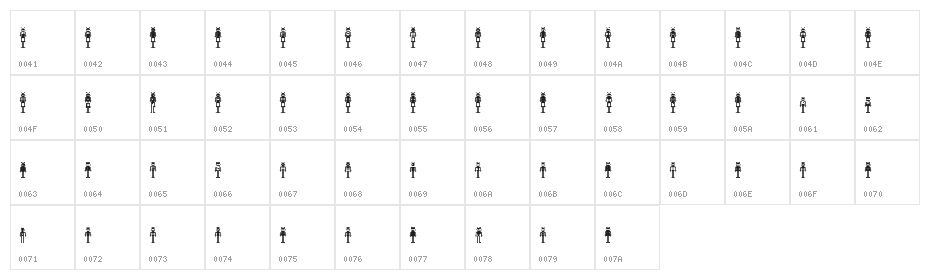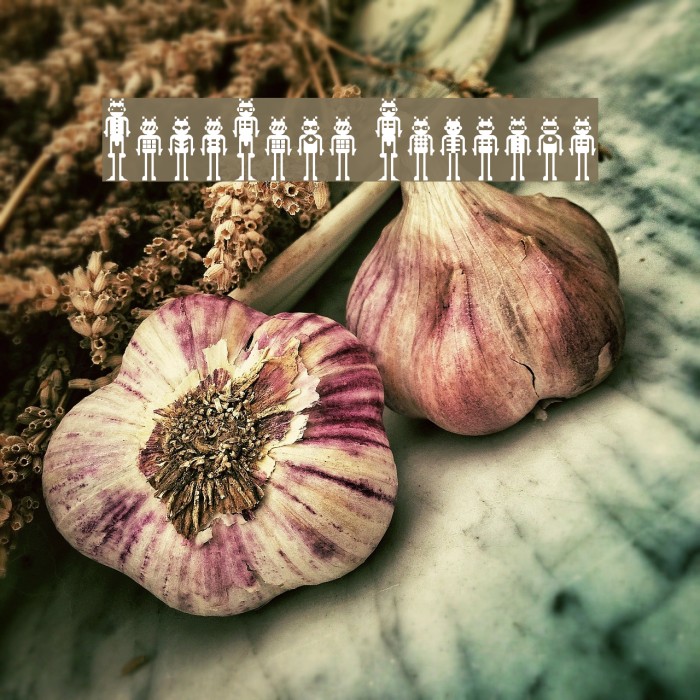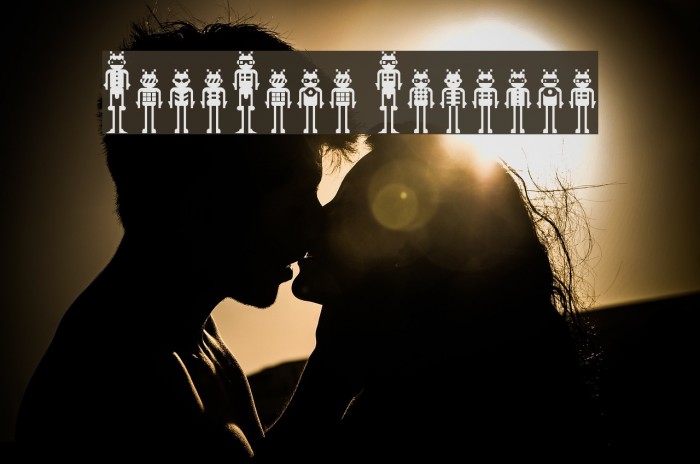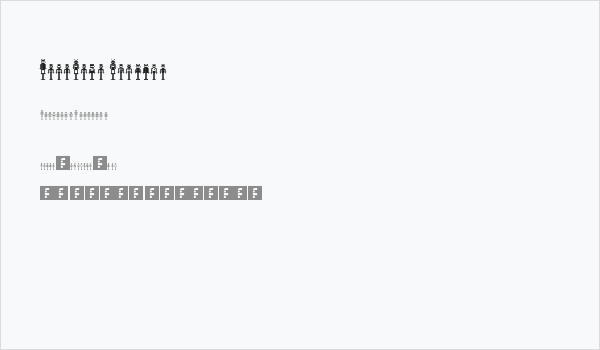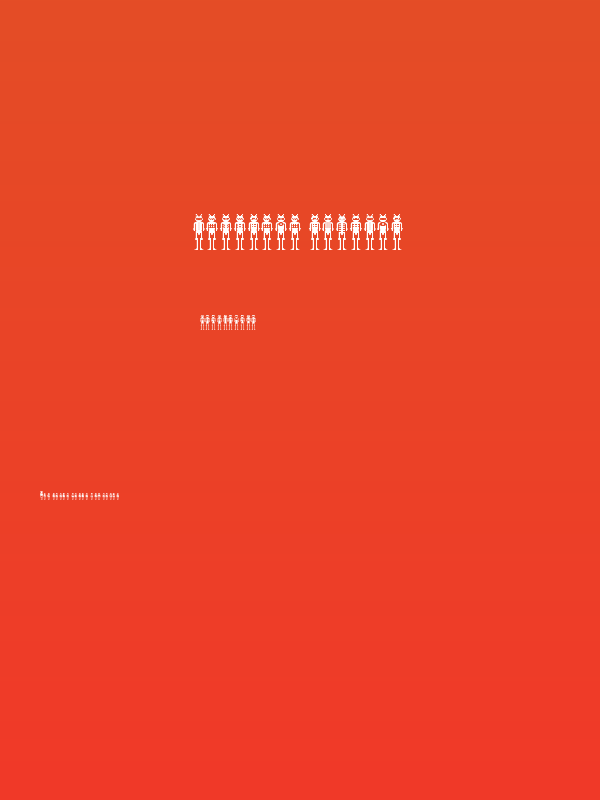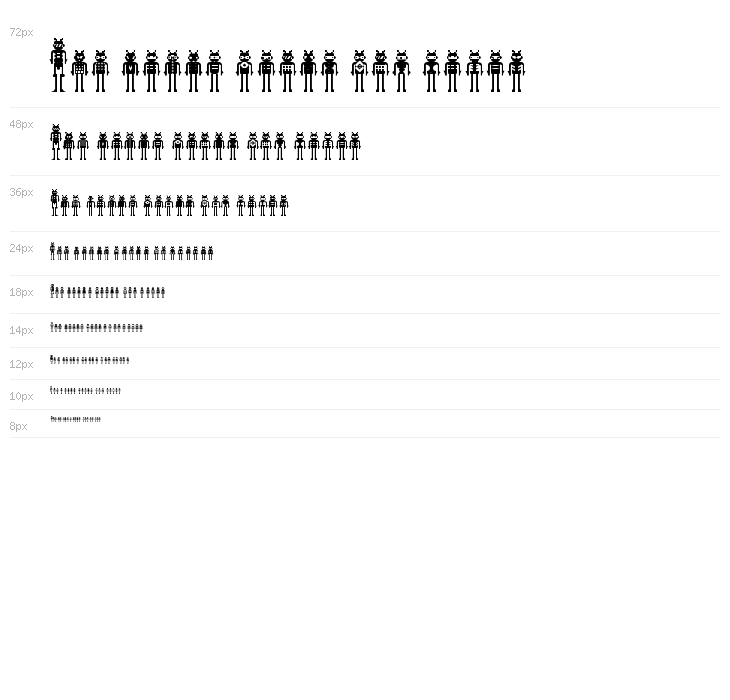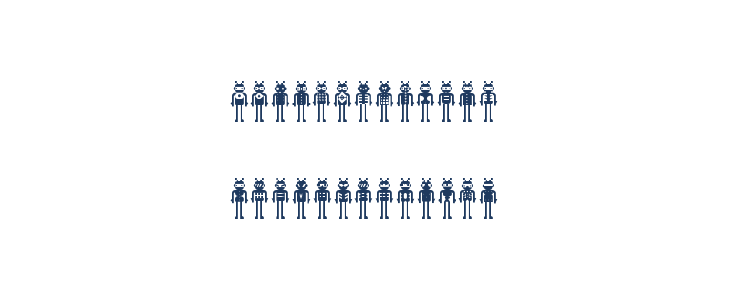
LostRobo Regular Font
| Stile generale | Futuristic, Playful |
| Caso d'uso | Logos, Posters, Creative Titles |
| Progetti proposti | Ideal for tech-themed designs, children's books, video game graphics, and creative branding. |